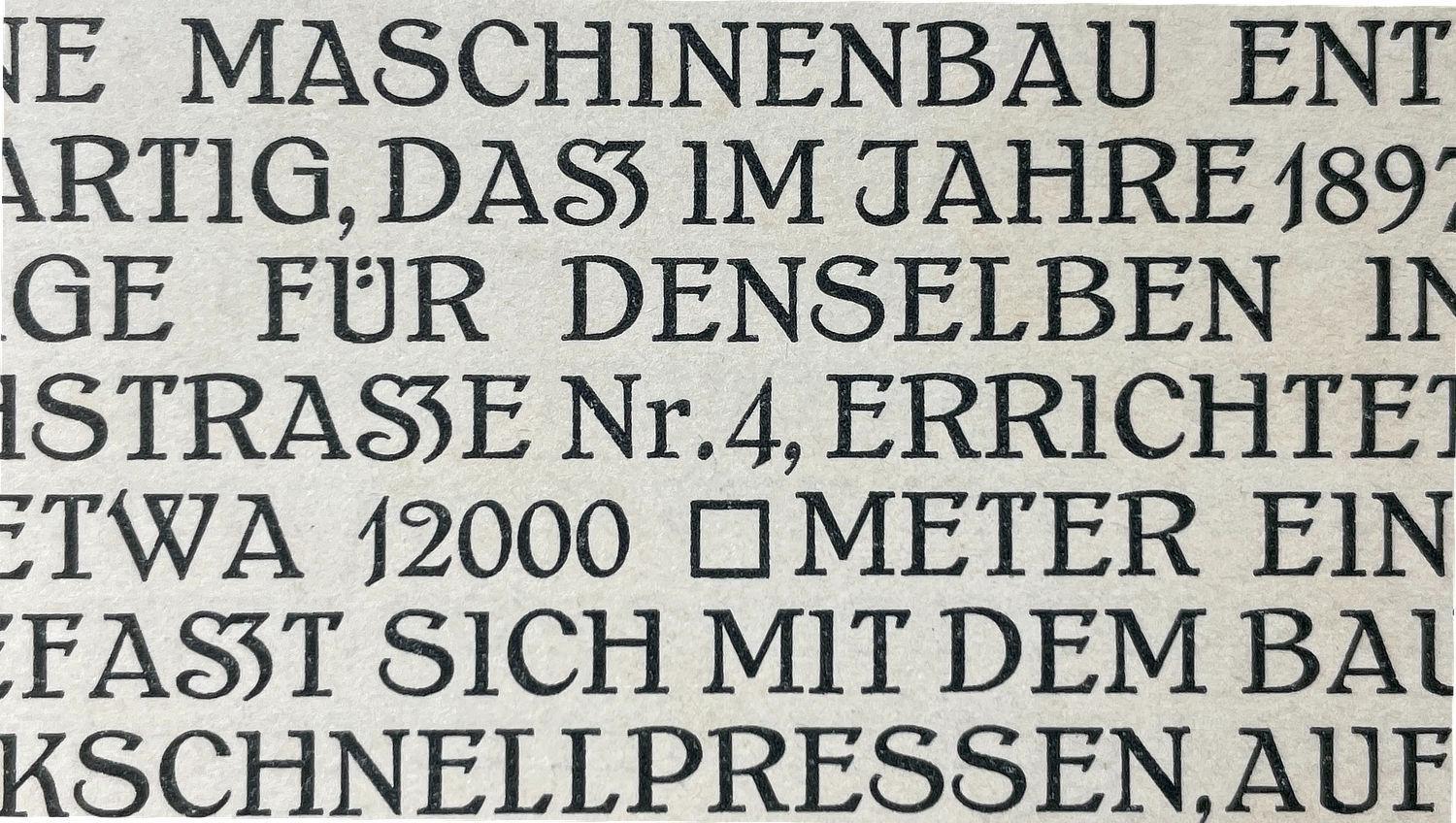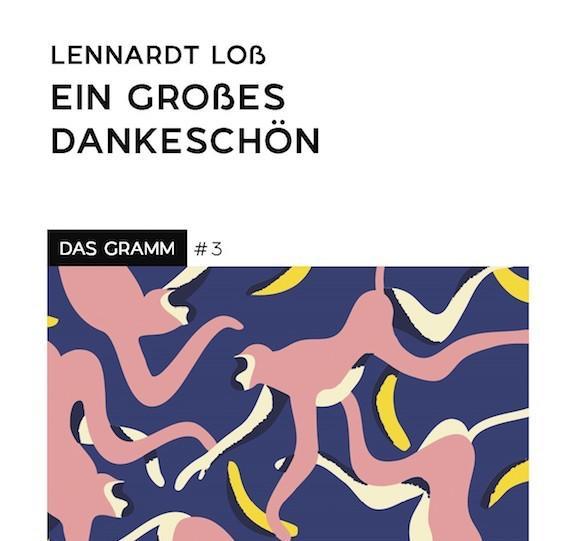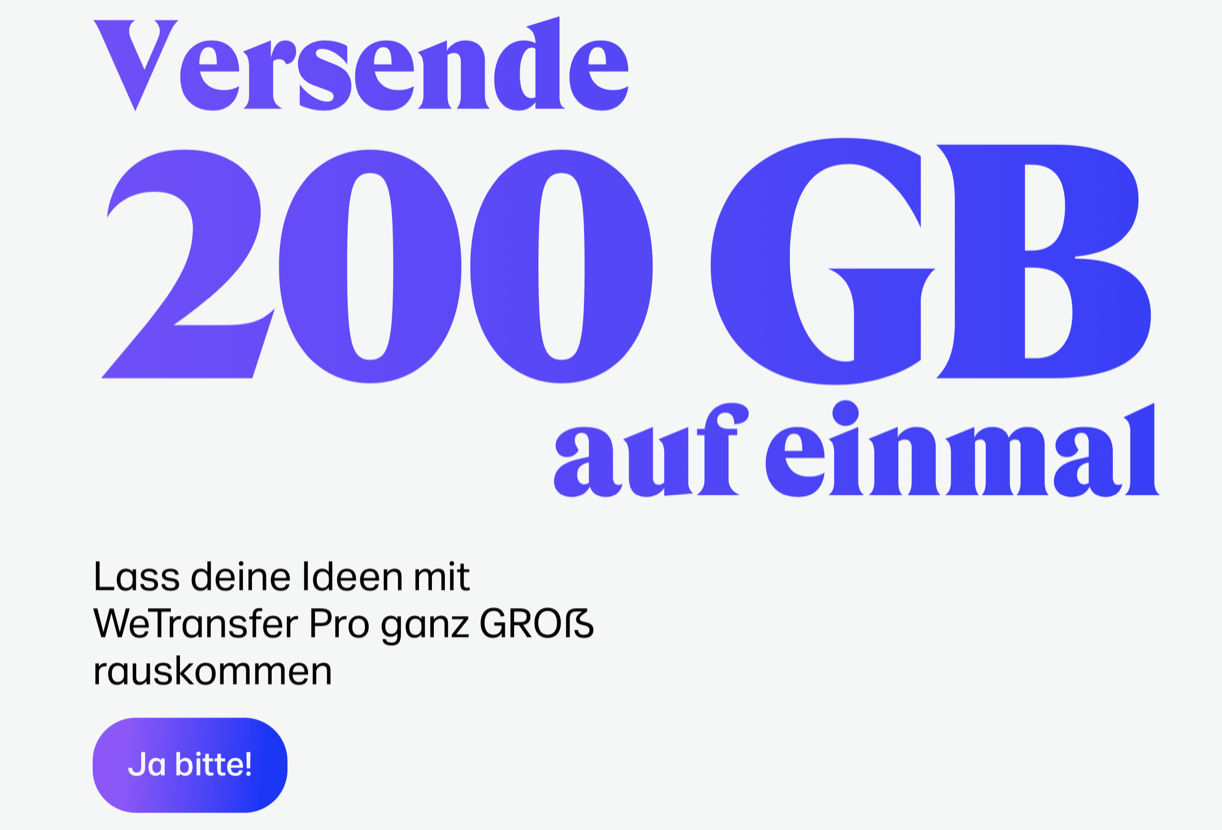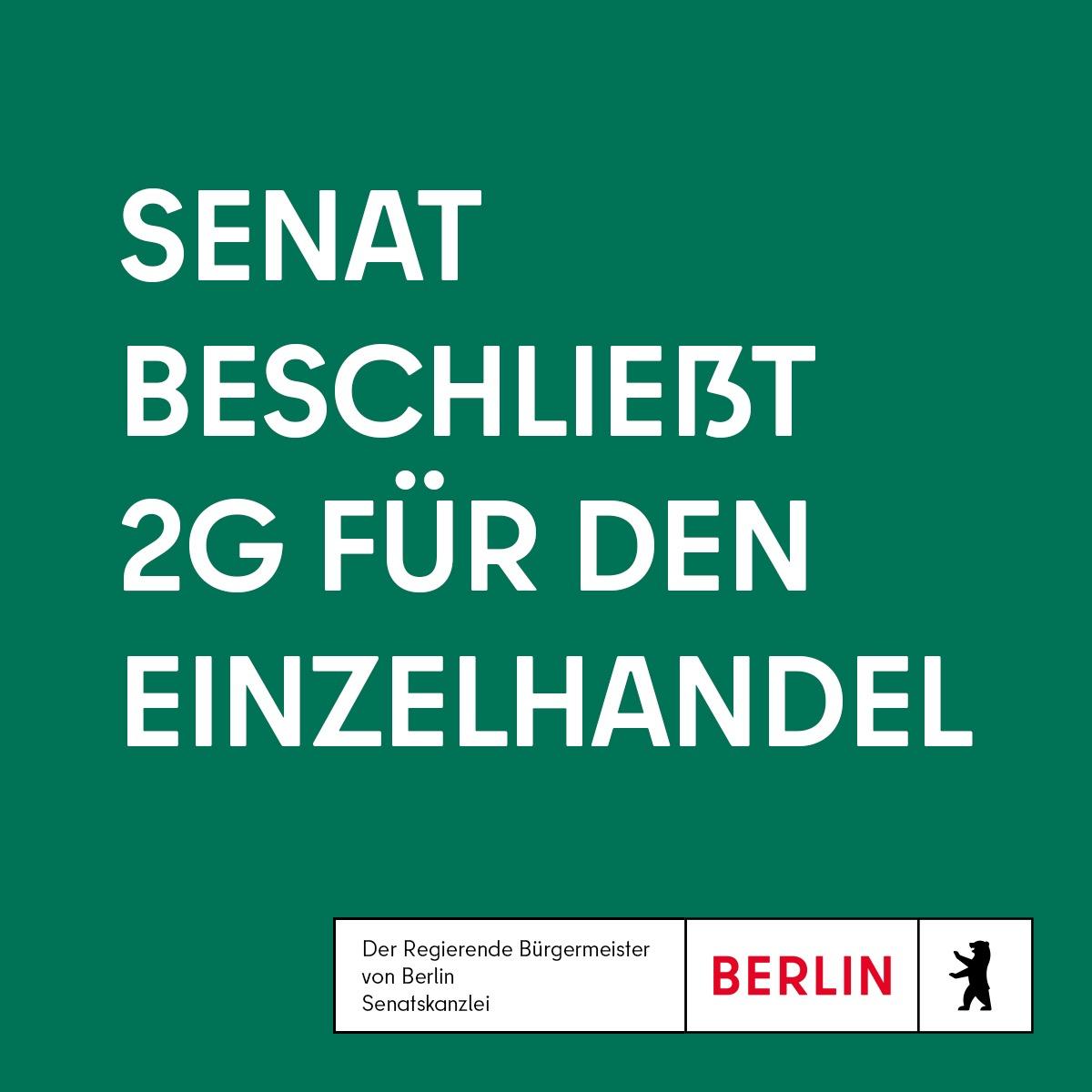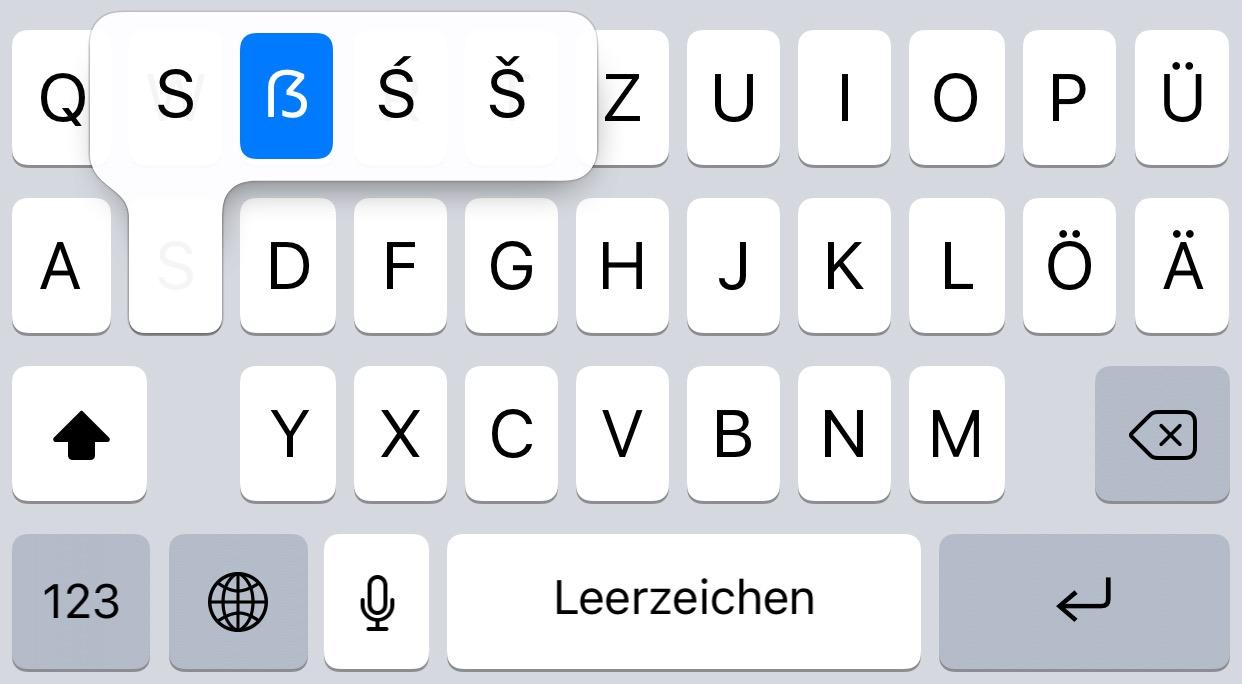
Kurios auch die Schreibweise für "Quadratmeter".
Kennt zufällig jemand den Namen dieser Schrift? Sie wird im Vorwort zur S&G Hauptprobe (1912) verwendet, und wird gewiß irgendwo im Buch behandelt; ich bin aber im Moment zu faul zum suchen.
Das Quadratmeter ist ja zu lustig 😄 und ich mag das versale Eszett irgendwie. Hat das schon einen Namen? Und die Ü-Punkte sind einfach nur :biglove:
Danke Ralf! Also die Salzmann-Antiqua ist es. Gibt es anscheinend (noch) nicht digital ;-)
Schelter & Giesecke Schriftprobe 1932
Wenn jetzt bitte noch jemand den Machern der Fernsehshow "KLEIN GEGEN GROSS[!]" auf die Sprünge helfen könnte...
Irgendwie duckt sich da das ẞ aber ein wenig schüchtern weg. Wirkt als fühlte es sich noch nicht ganz so erwachsen wie die Typen davor
Im aktuellen maiLab-Clip „Corona-Endlosschleife – Kommen wir da jemals wieder raus?“ (FUNK) gibt es auch eins à la schmaler DIN (siehe: Timestamp 5:09). Aber ob sich das Wort als mustergültiges Beispiel verwenden lässt, steht auf einer anderen Scheibe Käse. (Ich poste das aus aktuellem Anlass trotzdem mal.)
Das Wort könnte man reservieren für Muster von Schriften, deren Versal-ẞ man sch… findet.
Welches ist gemeint?
Ein Universal-ß? Für ein großes zu klein, für ein kleines zu groß?